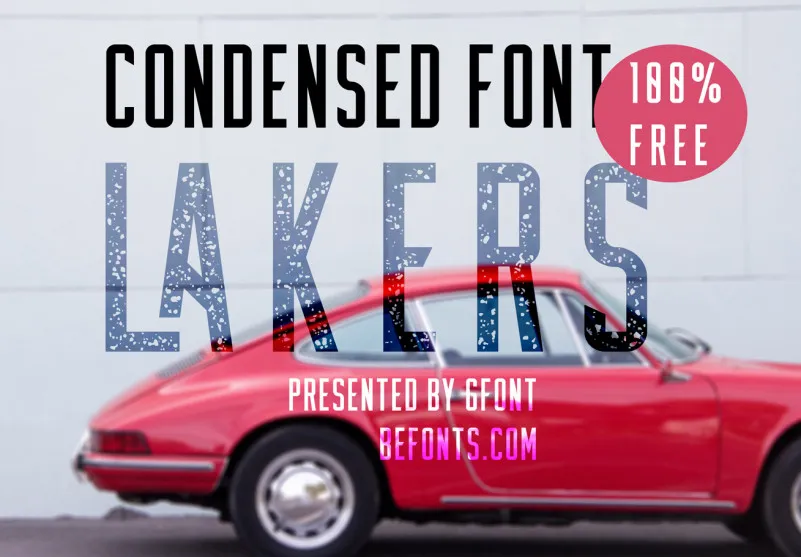
Lakers Free Font é uma fonte de tipo sans-serif compacta e moderna, perfeitamente adaptada para múltiplos usos. Suavemente clássica, ela transcende a simples função do design, servindo como um excelente recurso para criações variadas. A sua natureza all-caps distingue-a dos demais, criando impacto em quase qualquer projeto. Desde postais carinhosos e logo vintage até editorial, capas de revistas e rótulos em lojas, a fonte Lakers atende a uma vasta gama de aplicações. Sujeitosa aos requisitos comerciais, essa fonte também está disponível para uso pessoal. Aprecie e descubra como ela pode transformar seu design. Se procura mais fontes semelhantes, o BeFonts é um excelente recurso.
Designer: Gfont